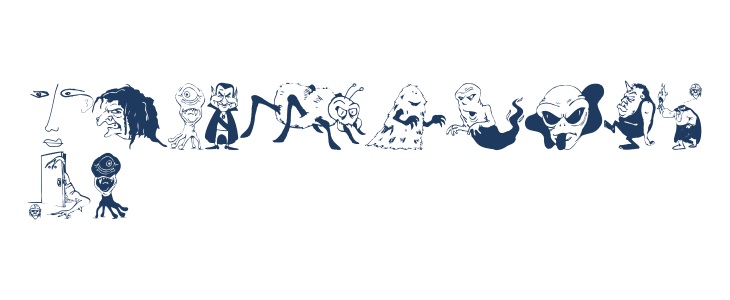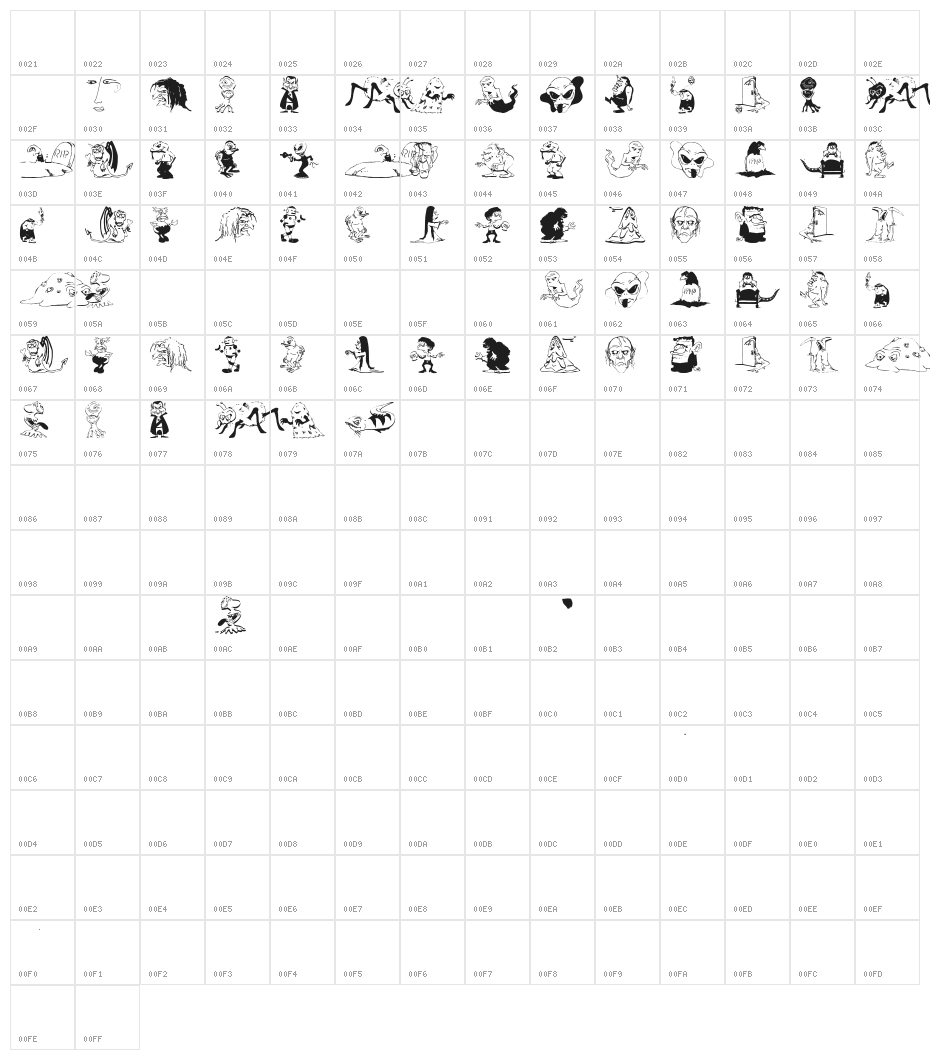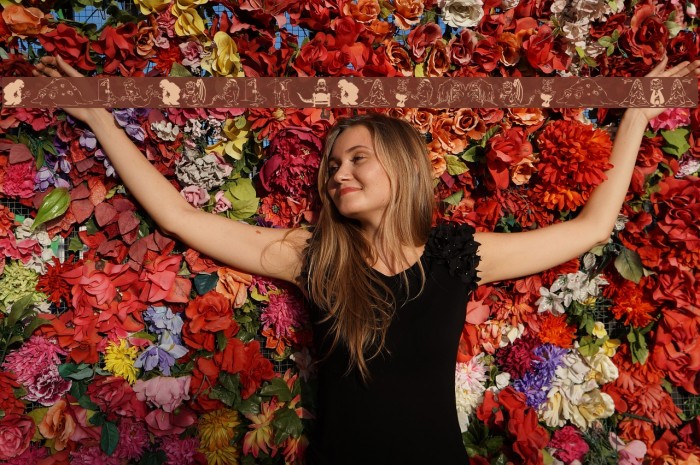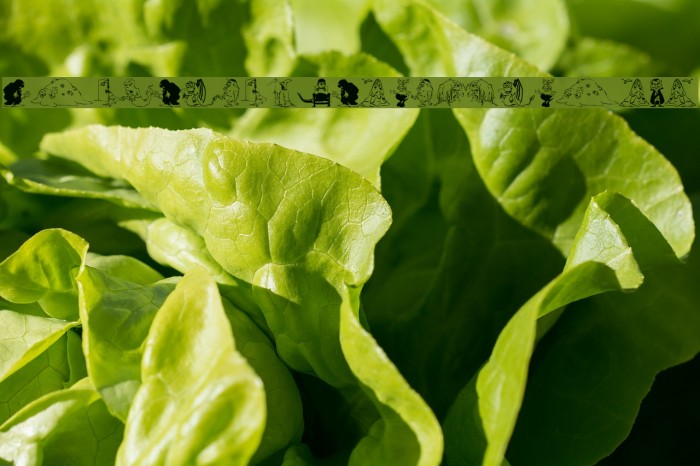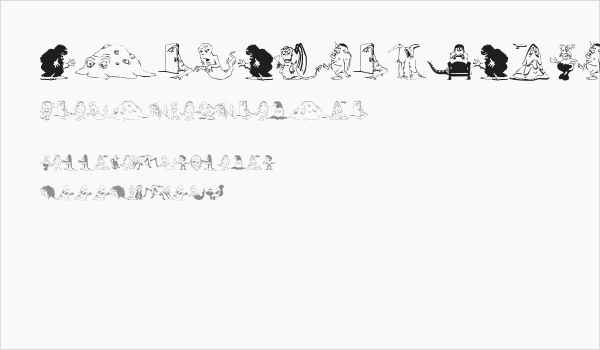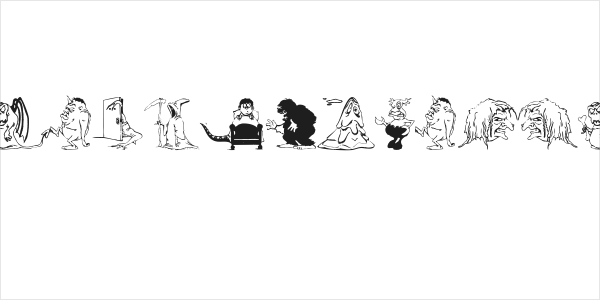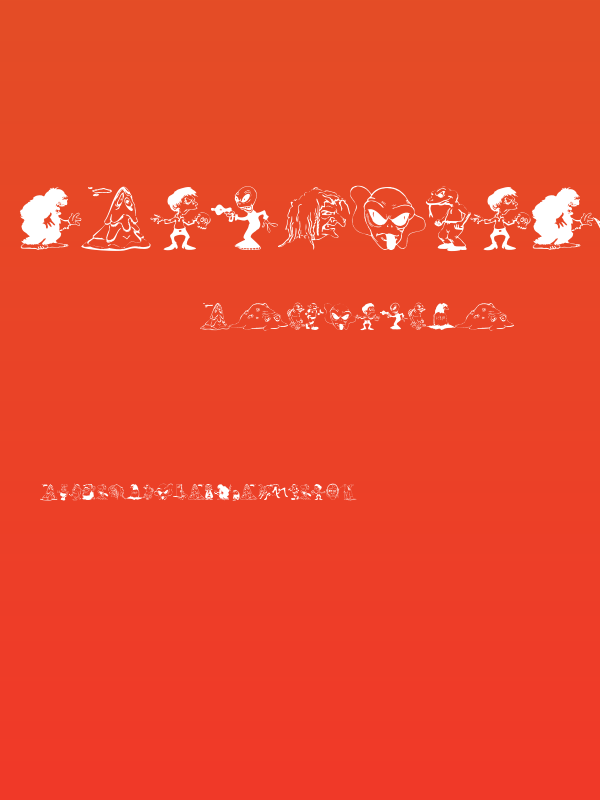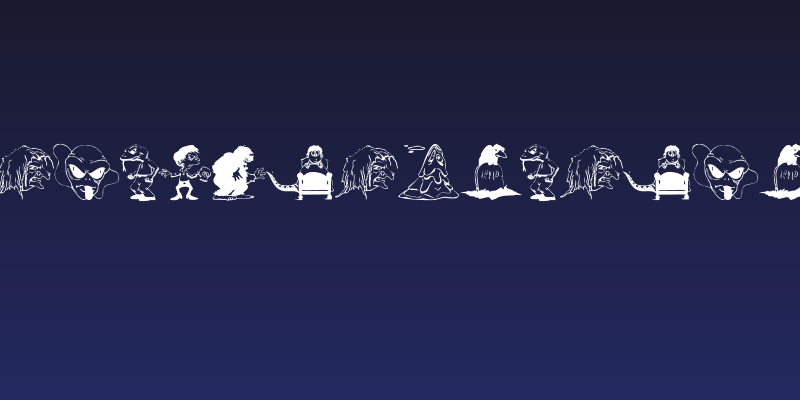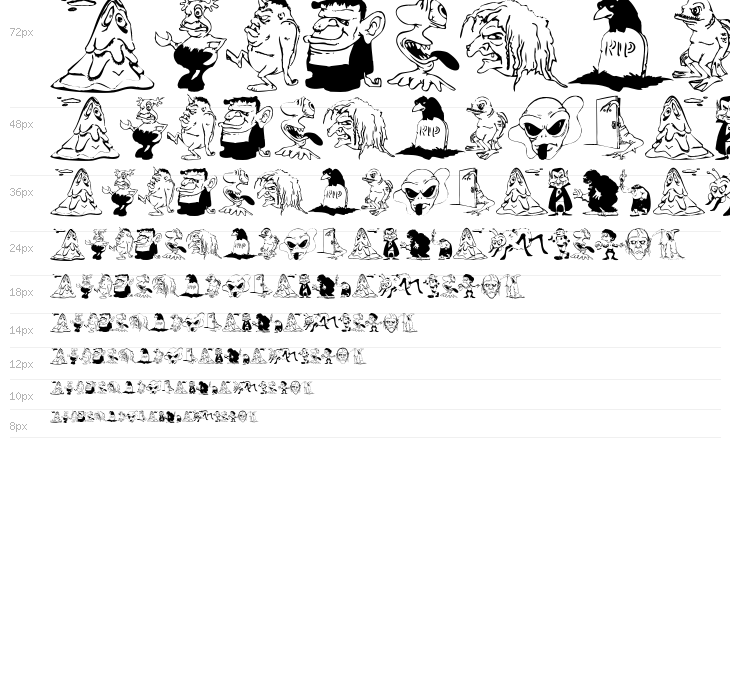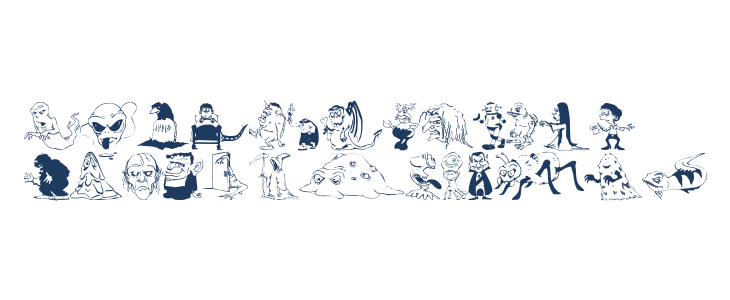
StrangersInTheNightTwo Font
| Projets proposés | Ideal for Halloween-themed designs, children's books, party invitations, and any project requiring a playful and imaginative touch. |